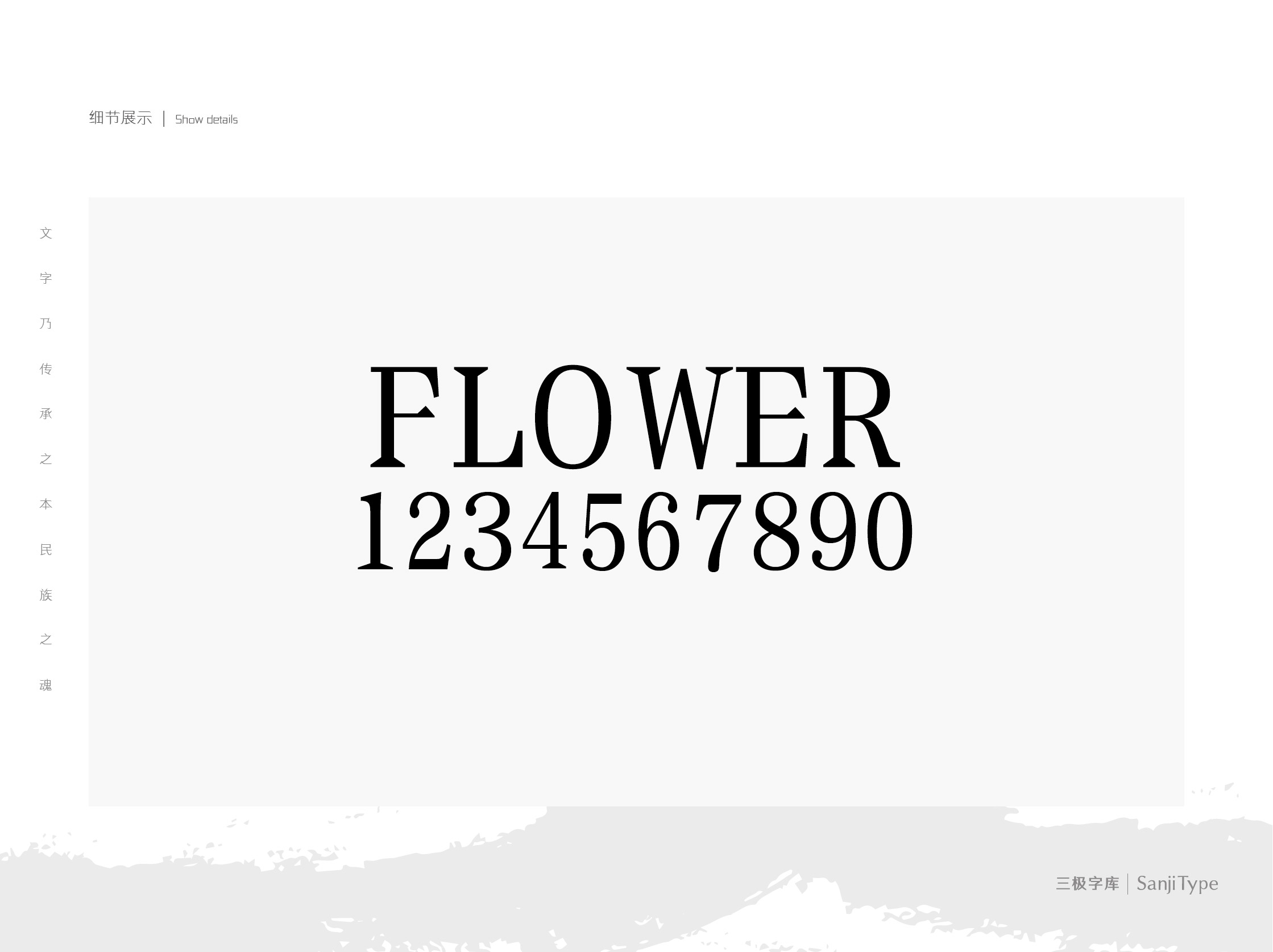
三极花朝体家族
三极花朝体 纤细
三极花朝体 细
三极花朝体 中
三极花朝体 中粗
三极花朝体 粗
三极花朝体
三极花朝体创意来源于中国传统节日——花朝节,指中国百花的生日。这款字体在横平竖直的笔画中加入弧度,彰显出复古优雅的传统韵味。粗细适中,疏密布局合理,清晰爽目,遒劲有力神韵超逸。用于内文中规整又不失活跃感,让人印象深刻,适用于各种书写印刷文本需求,是款审美价值与实用价值兼备的字体。